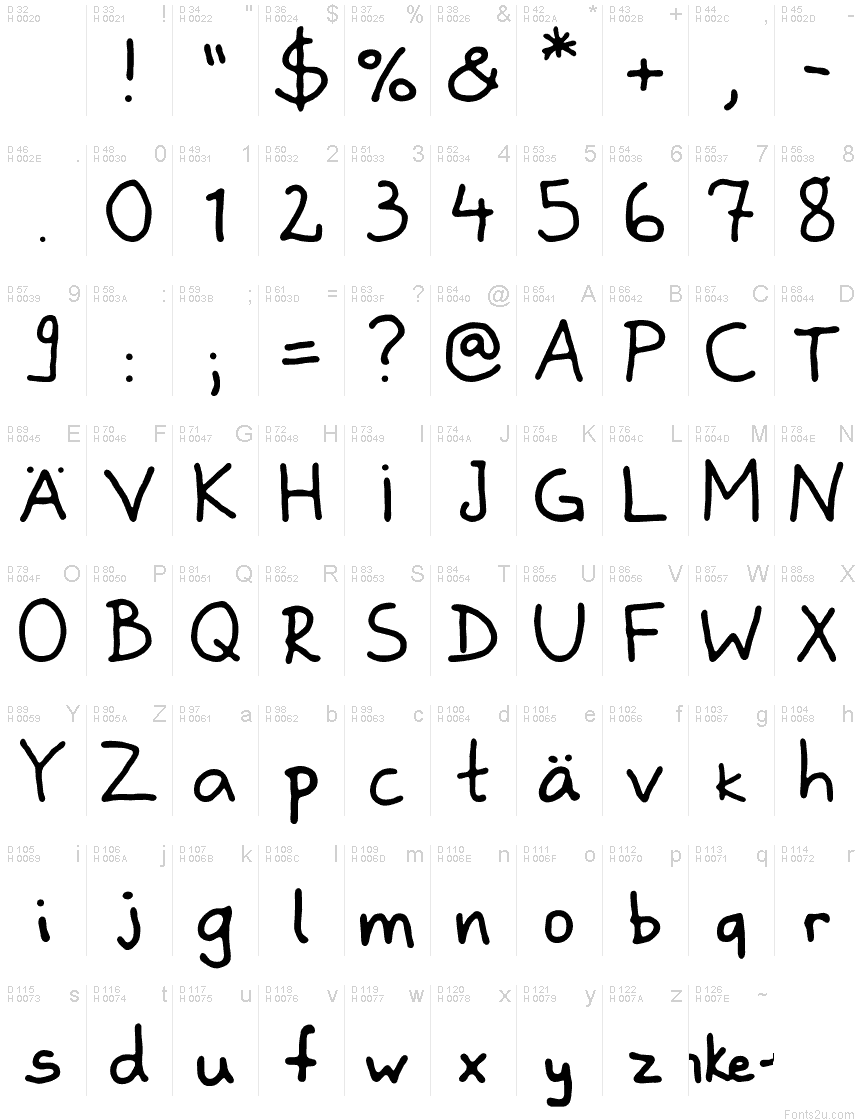
Zladdi od Anke Art to darmowy, zaokrąglony krój pisma odręcznego o swobodnym, przyjaznym rytmie. Litery wyglądają, jakby zostały narysowane jednym pociągnięciem, z miękkimi liniami, dynamicznymi łączeniami i lekko nierówną wysokością, co nadaje im ludzki, nieprzekombinowany charakter.
Sprawia to, że jest to naturalny wybór na okładki książek dla dzieci, menu w kawiarniach, opakowania rękodzieła, tytuły w albumach czy nieformalne nagłówki blogów, gdzie ten darmowy font wnosi ciepły, domowy klimat bez przesadnej słodyczy. Świetnie sprawdza się także w krótkich postach w mediach społecznościowych, na etykietach i w swobodnym brandingu, ponieważ szerokie krzywe i proste formy sprawiają, że tekst jest luźny i bezpośredni.